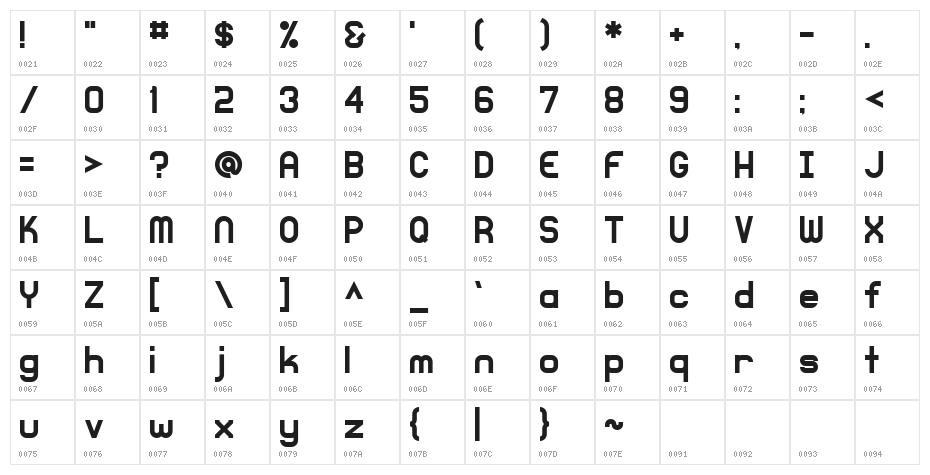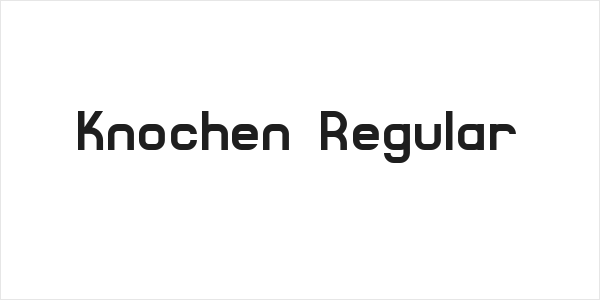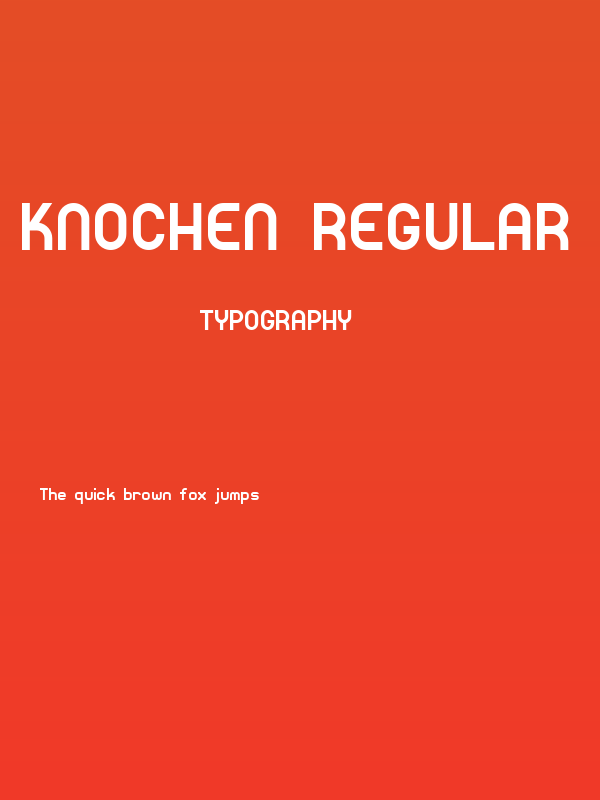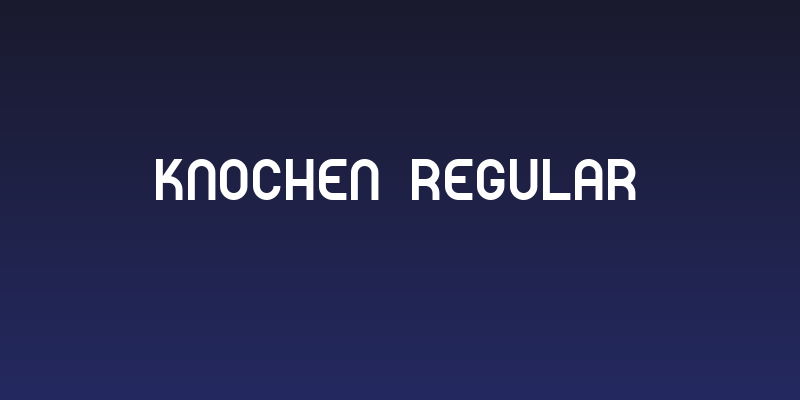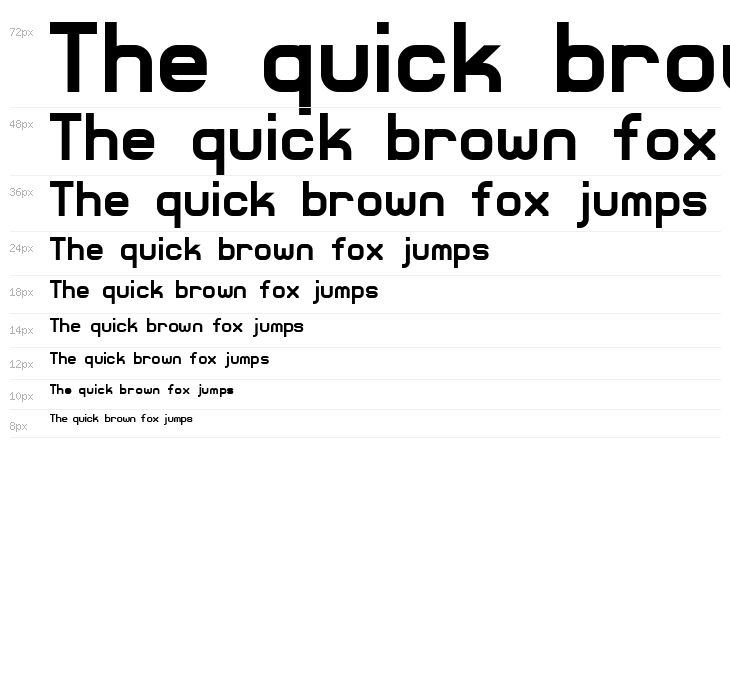
Knochen Regular Font
✎ Thick
| Proyectos propuestos | Ideal for branding, headlines, posters, and digital interfaces where a strong and modern look is desired. |